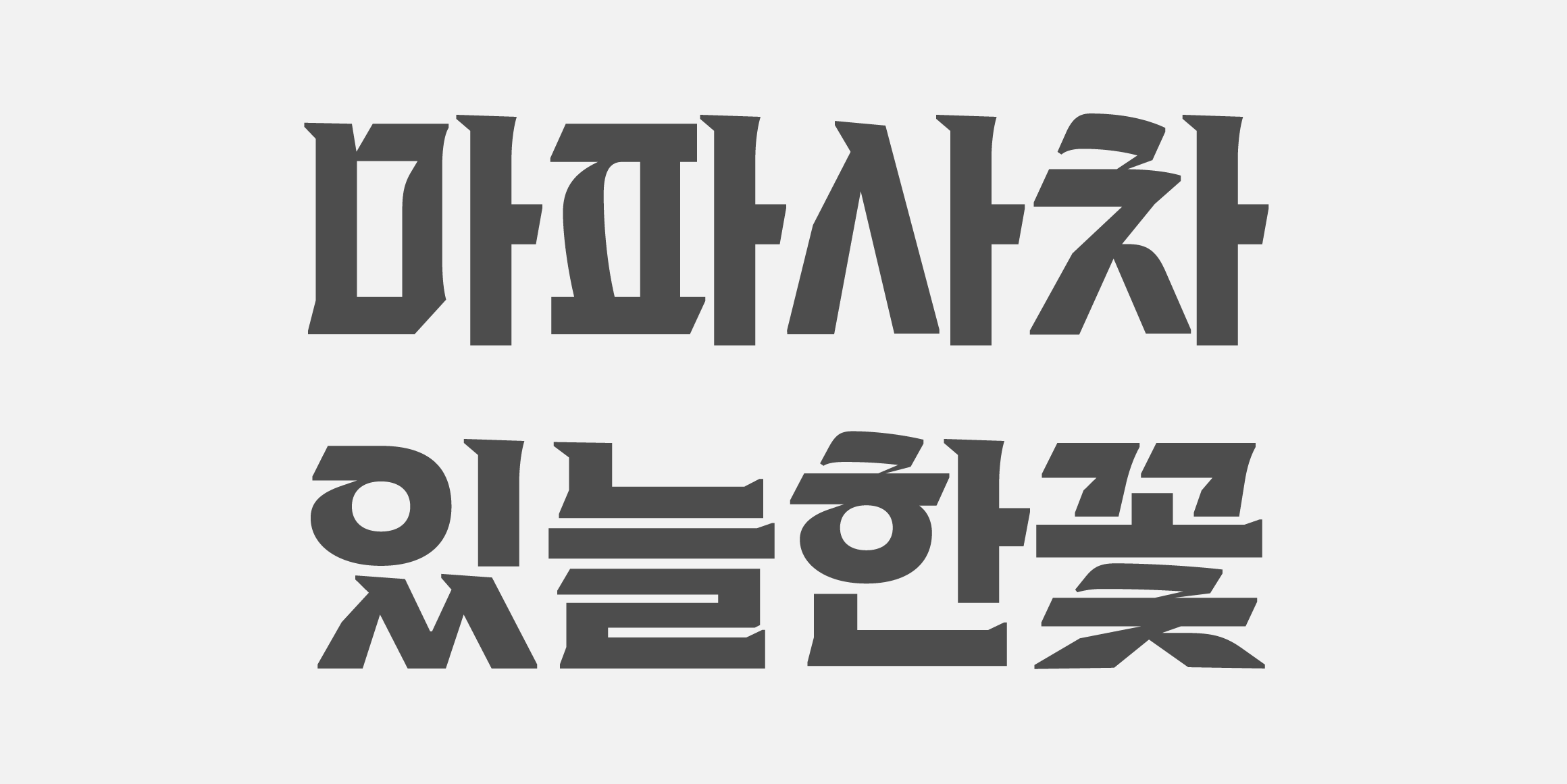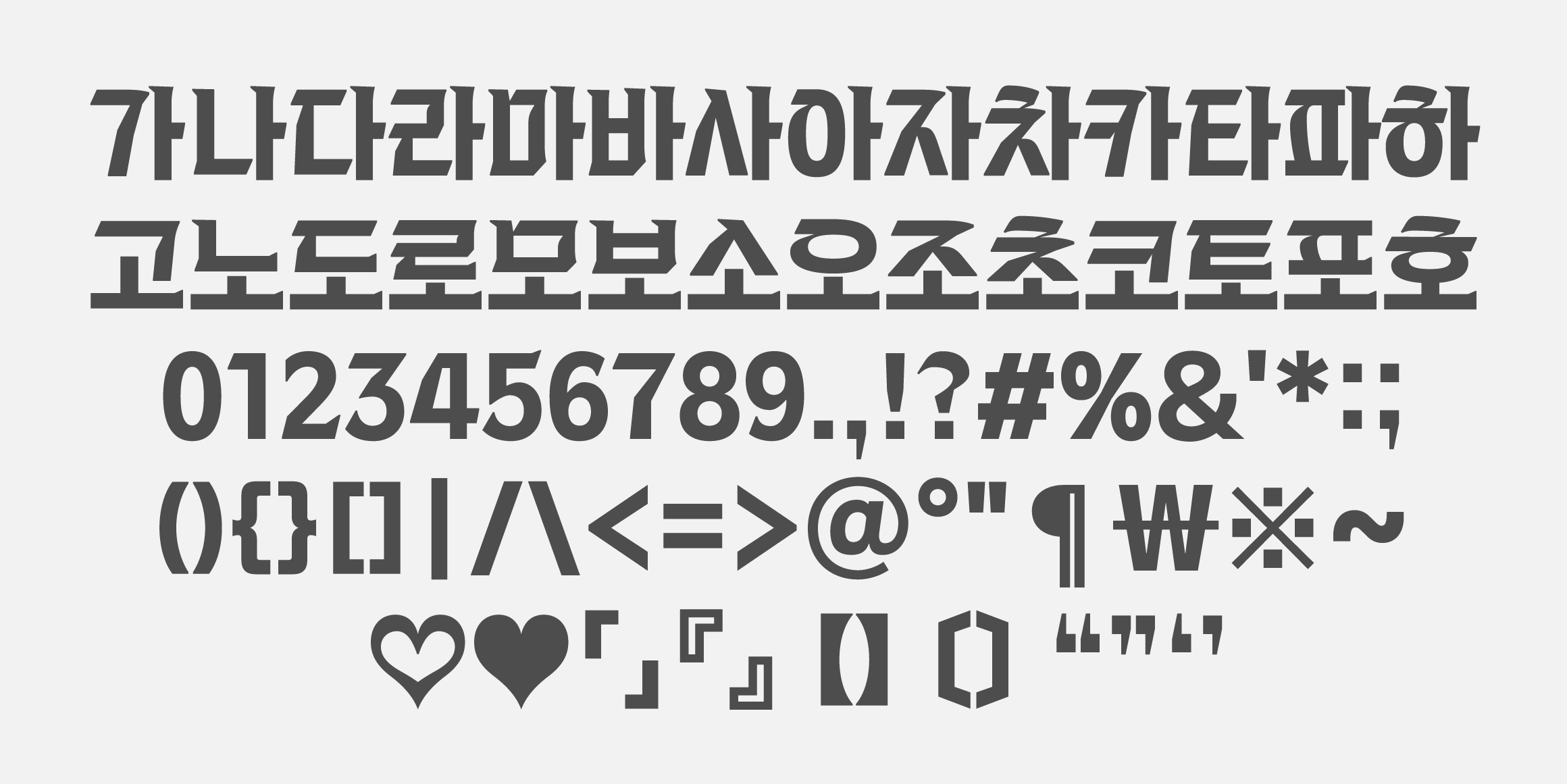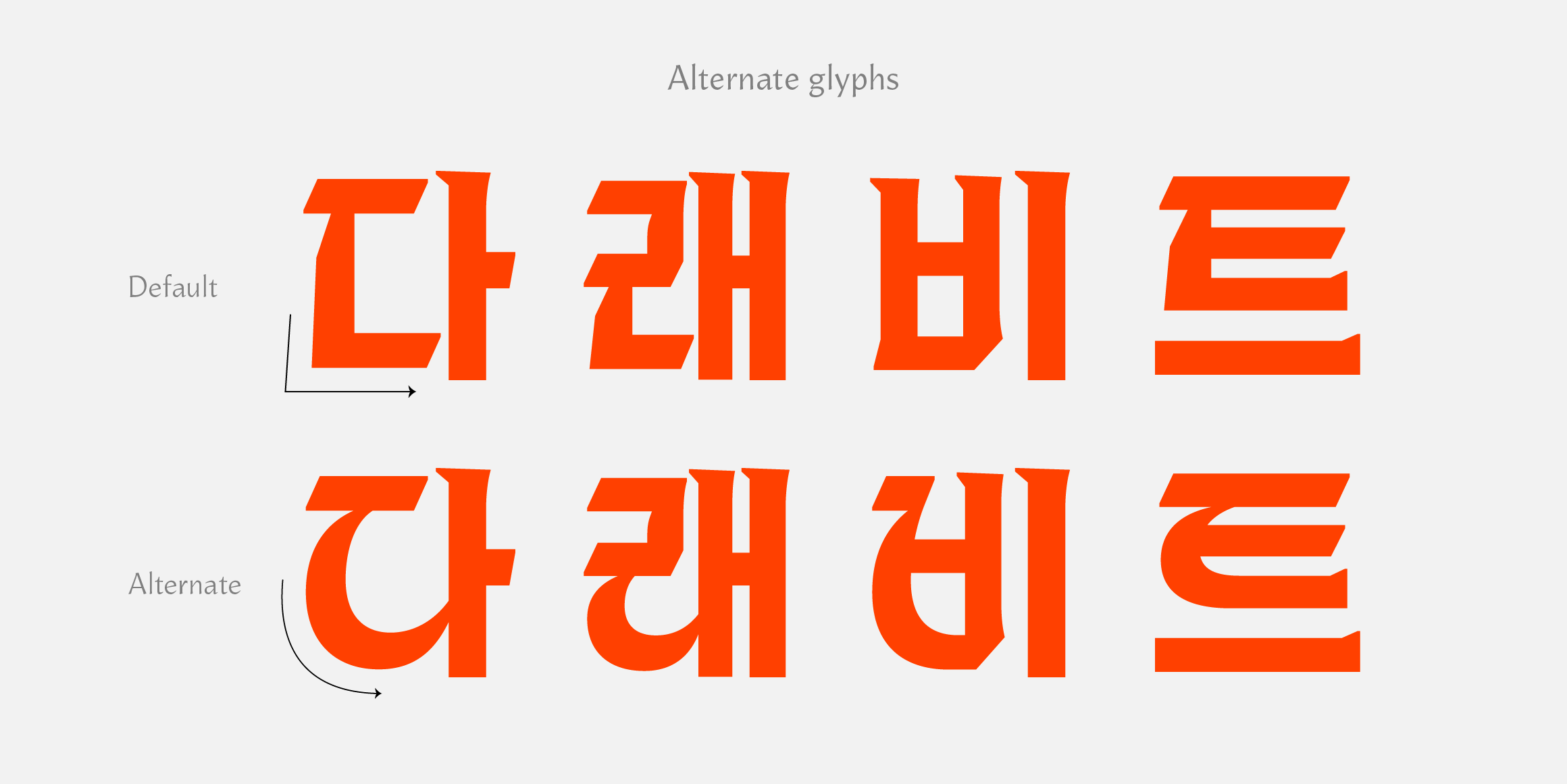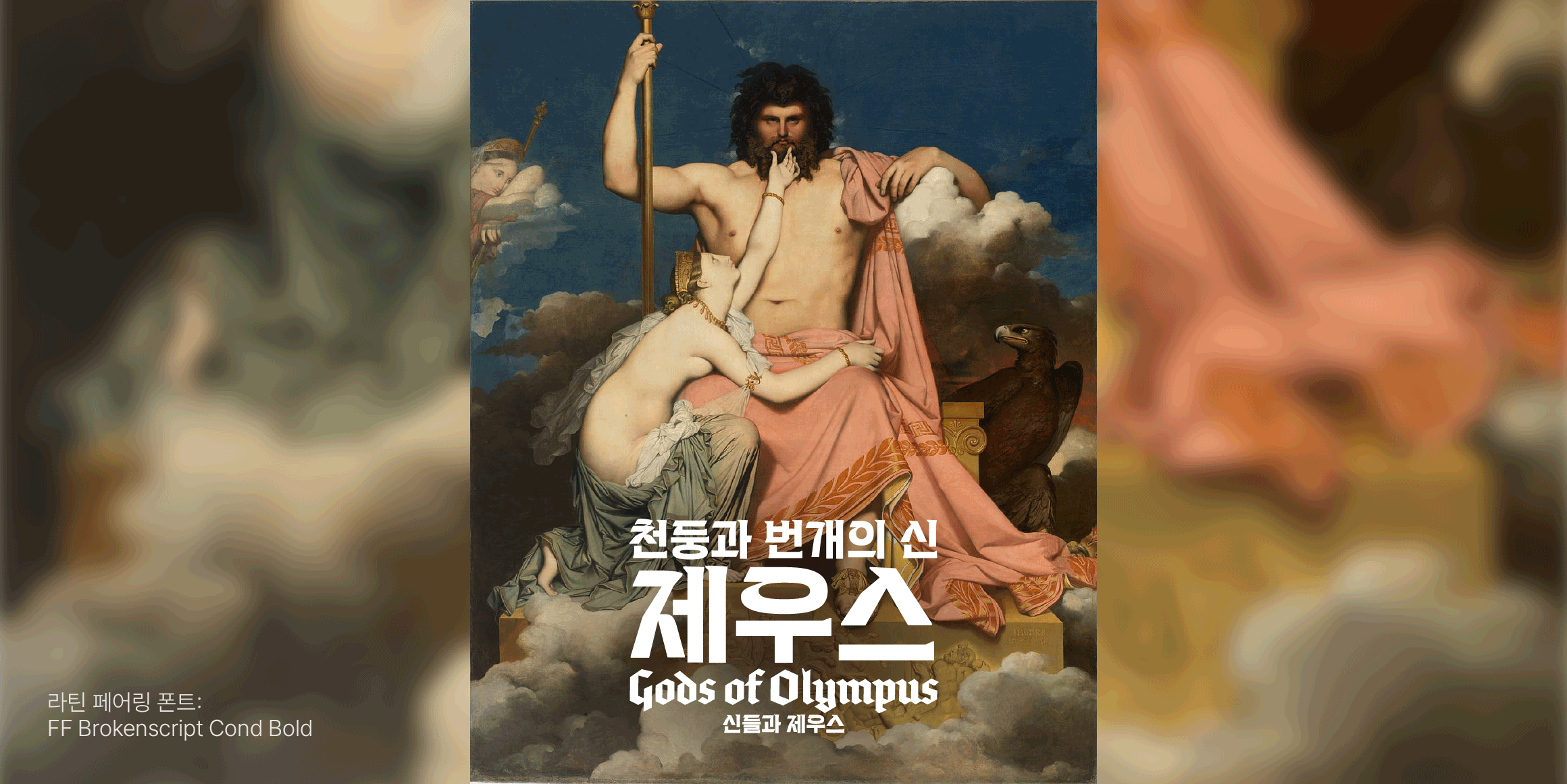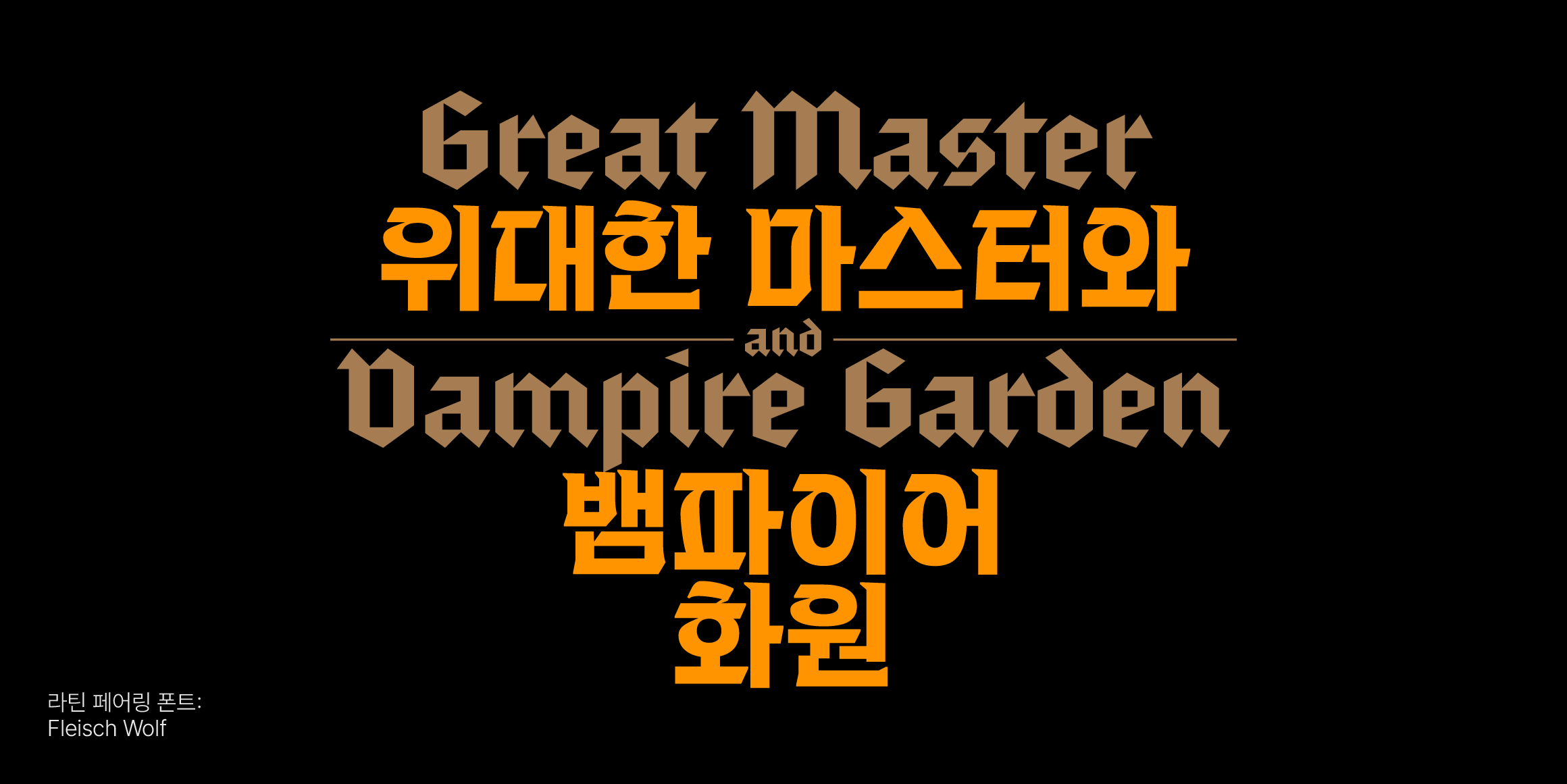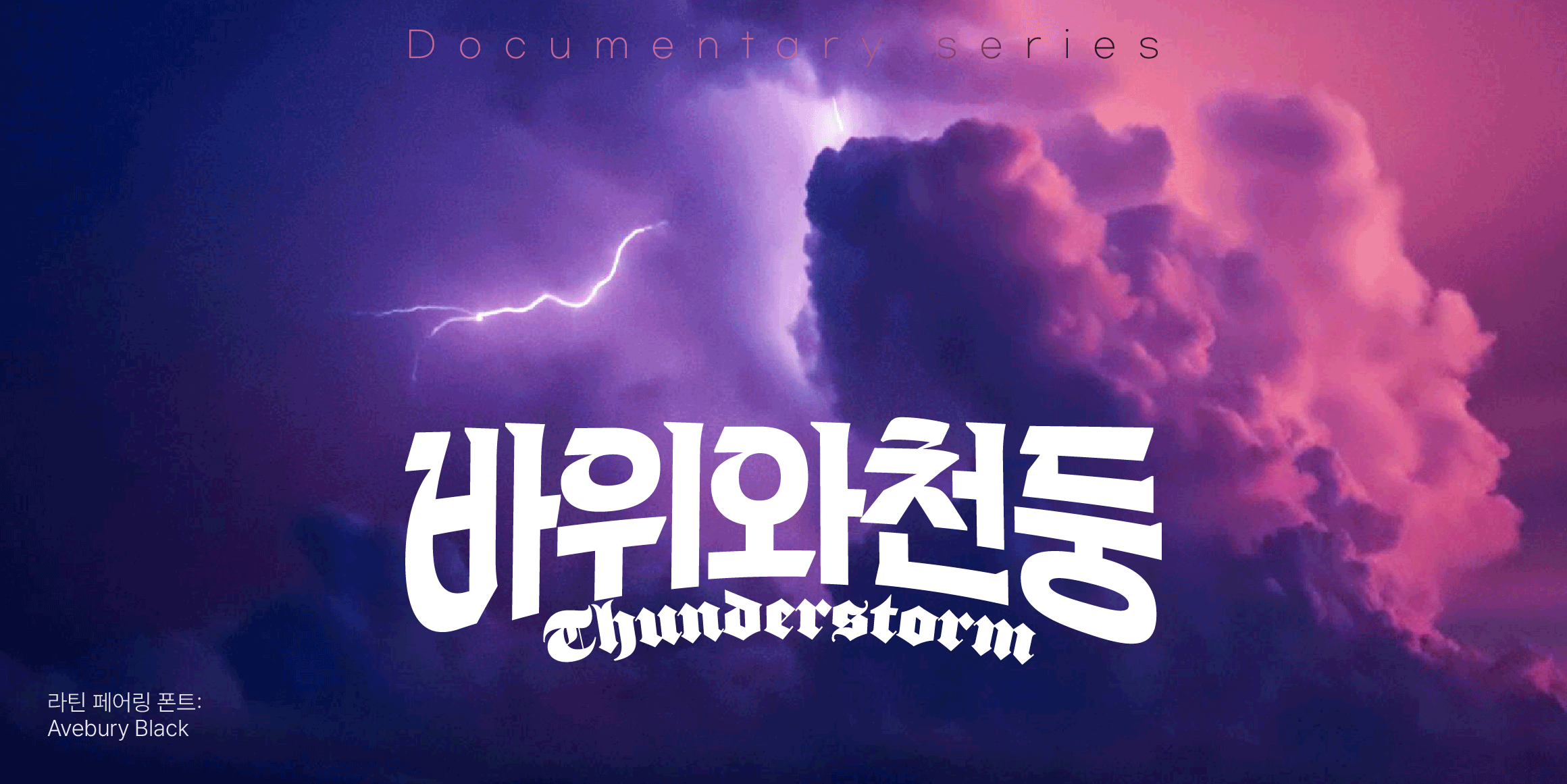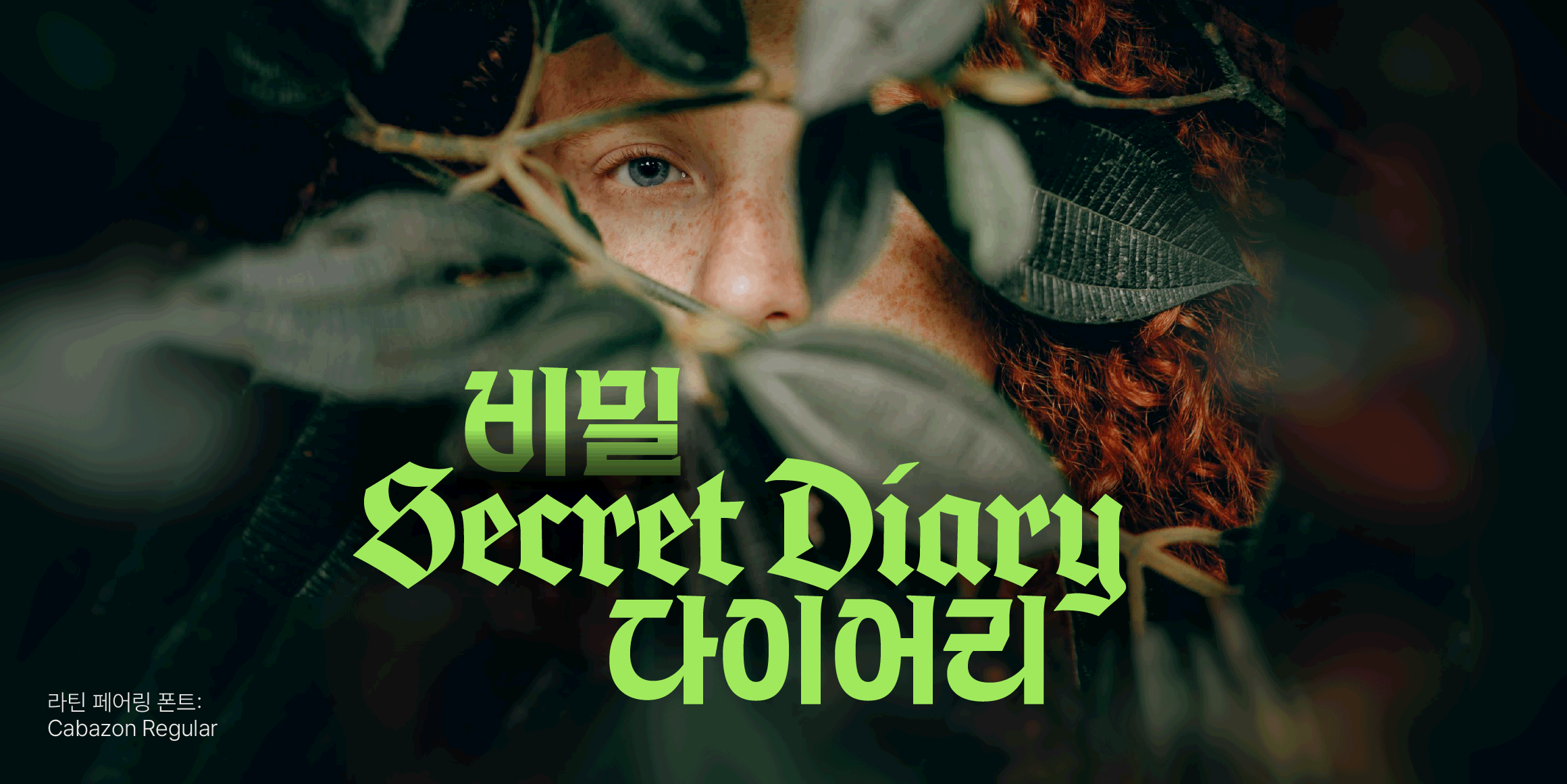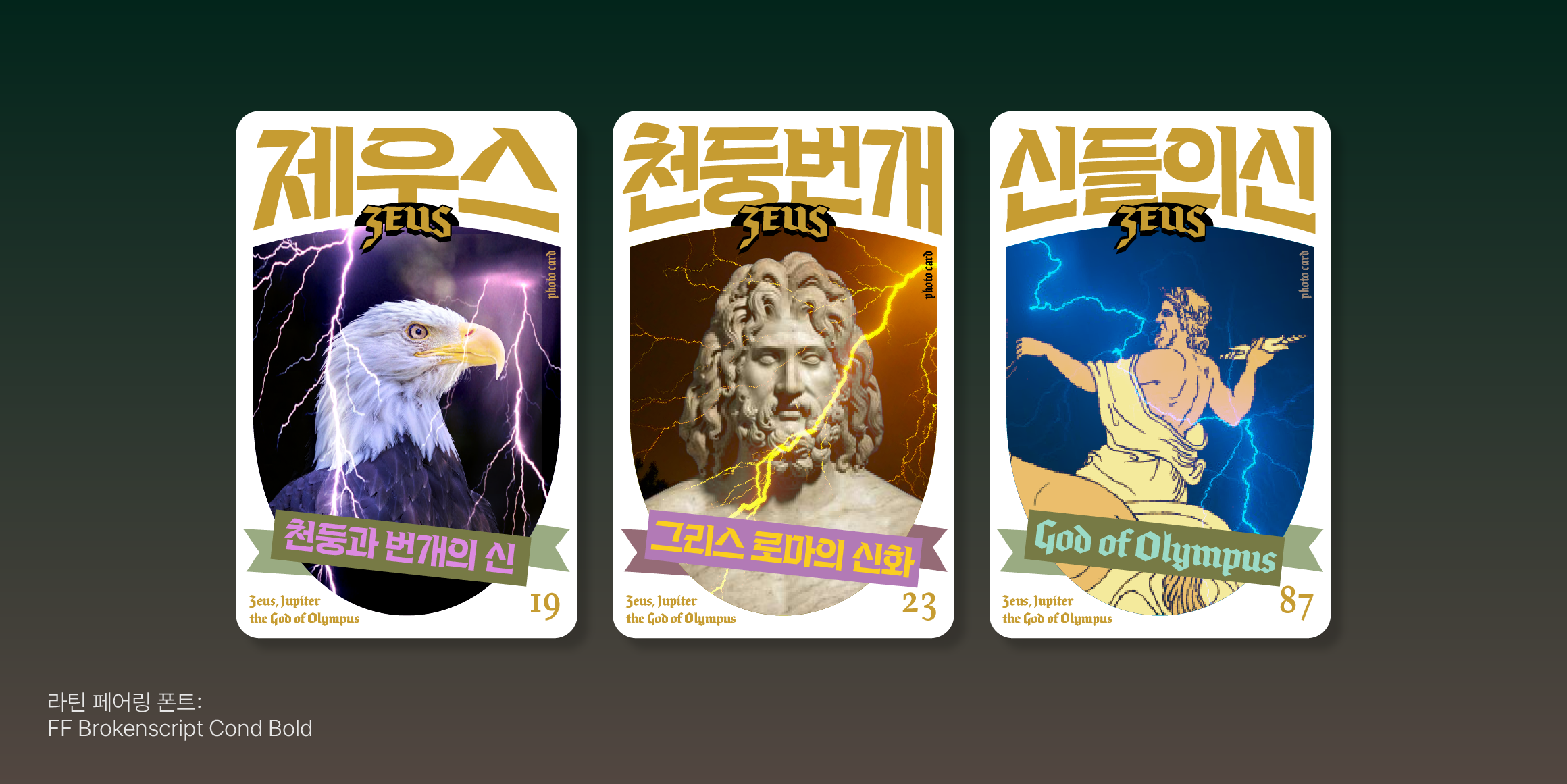
그리스 로마 신화에서 신들의 왕으로 표현되는 제우스(Zeus)는 천둥 번개를 자유로이 쓰며 강력함과 권위의 상징으로 그려집니다. 폰트 ‘제우스’는 두꺼운 획, 꽉 찬 네모틀 구조로 이루어져 강인한 첫인상을 가지고 있습니다. 브로드닙펜으로 썼을 때의 조형요소를 차용해 힘있는 분위기, 자연스러운 쓰기 형태를 강조했습니다. 짧은 문장과 단어, 큰 사이즈의 Display 용도에 맞도록 뼈대를 설계했고, 한글 모임꼴들이 같은 자폭(Width)을 가진 고정폭 구조로 만들었습니다. 주로 블랙레터 스타일의 알파벳과 페어링 했을 때 어울릴 수 있도록 만들었습니다.
한글 2,780자 내에서 대체 글리프를 지원합니다.
ㄷ,ㅂ,ㄹ,ㅌ 초성(첫닿자)는 기본적으로 단단한 꼴로 디자인되어 있지만, 오픈타입 피처 스타일 세트를 사용해 둥근 표현의 초성 스타일로 변경할 수 있습니다. 각 스타일 세트는 단독으로도, 여러 가지 함께 사용도 가능합니다. 아래 사용 가능 글자를 확인해 주세요.
• 초성 ㄷ 스타일 대체 (Chosung tikeut stylistic set)
• 초성 ㄹ 스타일 대체 (Chosung rieul stylistic set)
• 초성 ㅂ 스타일 대체 (Chosung pieup stylistic set)
• 초성 ㅌ 스타일 대체 (Chosung thieuth stylistic set)
- CT 제우스 / CT Zeus